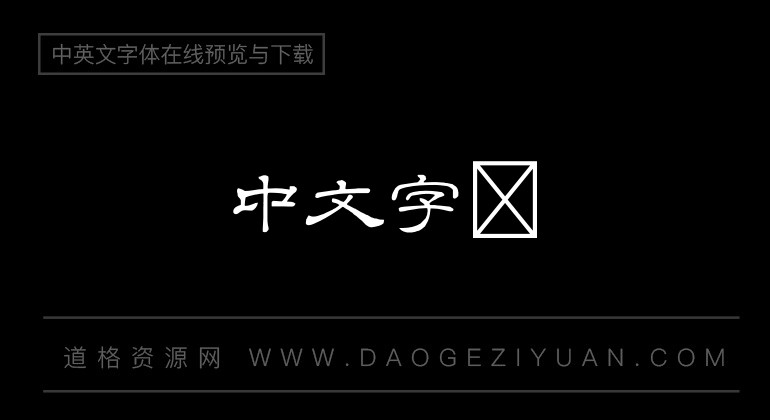
隶辨隶书体
隶辨隶书体是一种汉字书法字体,它是汉字书法的一种风格,它有着清晰明了的笔画,沉稳厚重的气质,给人以庄重、大气的感觉。它的笔画比较粗细相间,比较规范,给人以稳重的感觉。隶辨隶书体的字形比较规整,笔画比较粗细相间,比较规范,给人以稳重的感觉。它的笔画比较粗细相间,比较规范,给人以稳重的感觉,有着明快的笔画和清晰的线条,给人以清新的感觉。
隶辨隶书体是一款非常不错的手写艺术字体,具有很好的视觉感,适合于文化类的宣传设计、商业类品牌的广告和产品包装设计以及个性化文字排版等较多场景。